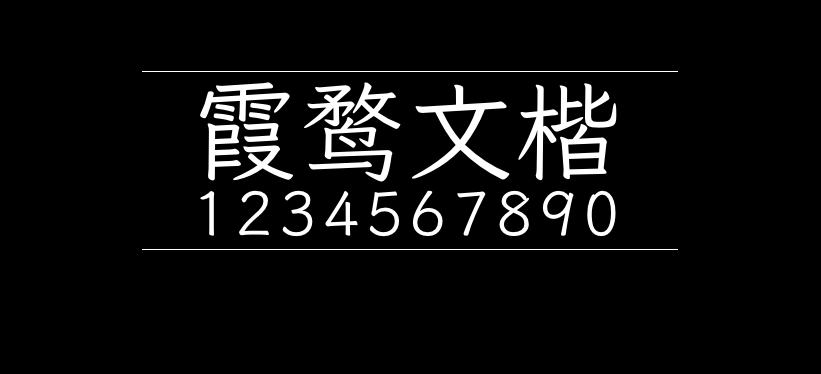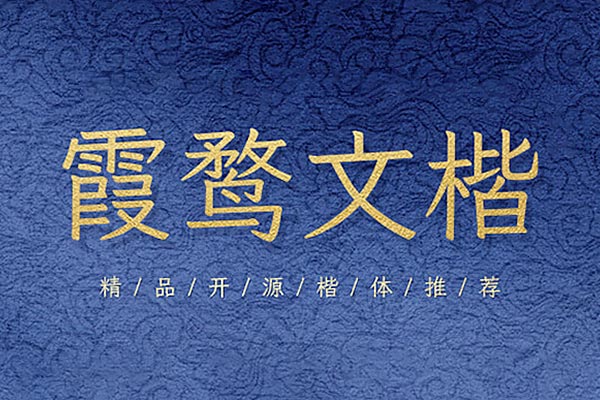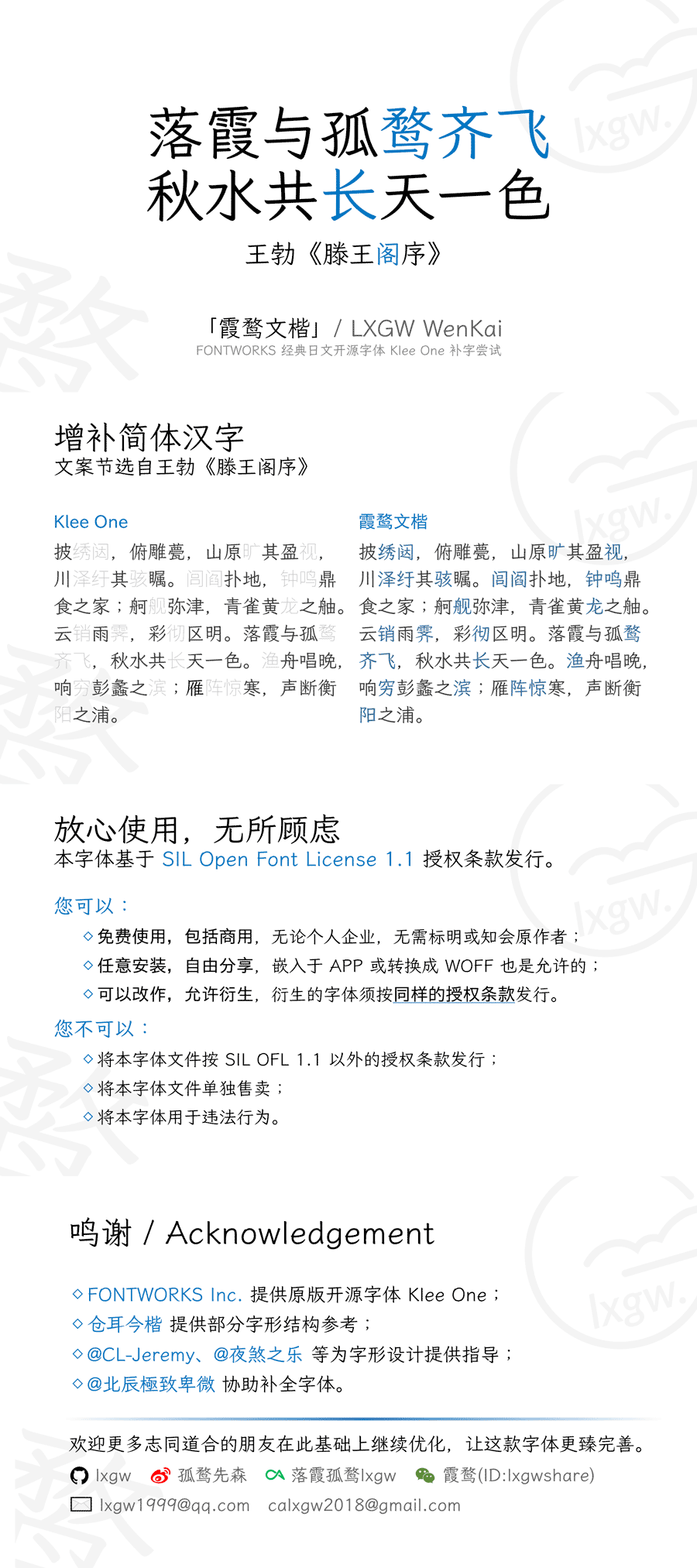
霞鹜文楷
霞鹜文楷是国内的字体创作者落霞孤鹜基于Klee One进行增补的一款的开源中文字体。
日本著名字体厂商Fontworks前端时间在GitHub上释出了7 款开源日文字体,分别为 Train、Klee、Stick、Rock-n-Roll、Reggae、Rampart 和 DotGothic16。其中的Klee有着日本教科书体的写法,兼有仿宋和楷体的特点,可读性高。一些DIY字体爱好者曾先后用仿宋、刻本仿宋、仓耳今楷补全这款字体,做为手机系统的美化字体移稙在 iOS、Android 等手机系统中,受到很多机友的欢迎。
不过这样补全的字体有一些不足之处:
1、原有字体和后补字体之间有着一定的差异,致使一些不同的文字(如Klee原有汉字与后补简体字)混排之后会有违和感。
2、由于补字所用的字体(如刻本仿宋、仓耳今楷等)为商业版权字体,补全之后不可用于商业用途,还会有侵权的风险。
鉴于此,落霞孤鹜开始了为Klee这一高质量的日文字体补全简体字的尝试。补全后的字体拟命名 「霞鹜文楷」。选取原字体 SemiBold 字重做为Regular字重。
目前,该字体已增补完成GB2312的6763个简体字,以及繁体中文 4808 常用汉字,基本不存在缺字现象了,喜欢的不要错过了!
更新记录:2021-07-19霞鹜文楷更新至1.004版本,扩展了字重,现在拥有细体、常规、粗体共3个字重。
更新记录:2021-07-22霞鹜文楷更新至1.005版本,增加了等宽字体Mono版本。
更新记录:2021-08-09霞鹜文楷更新至1.006版本,调整了 80 个字的字形。